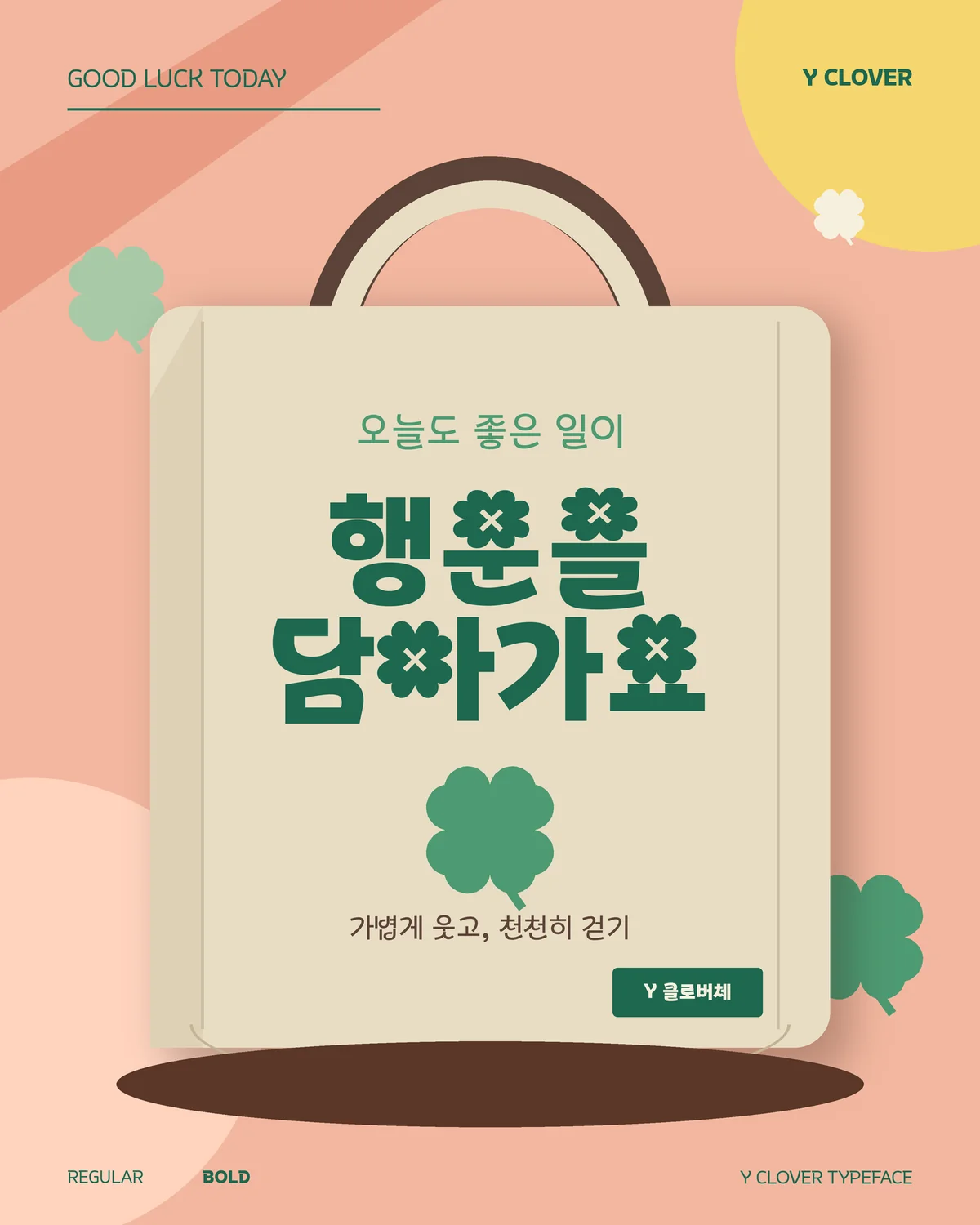
Y클로버체 — (주)케이티에서 배포하는 무료 폰트입니다. 네잎클로버의 형태를 자소에 녹여내 발랄하고 통통 튀는 인상을 표현한 장식 고딕체
KT의 청년 브랜드 Y 서체 시리즈 가운데 2023년에 나온 서체입니다.
모티브는 네잎클로버입니다. KT는 이 서체를 Y의 밝고 활동적인 모습을 네잎클로버에 담은 발랄하고 통통 튀는 서체라고 설명합니다. 행복과 행운이라는 클로버의 상징이 그대로 성격이 된 셈입니다.
굵기는 Regular와 Bold 두 가지이고 현대 한글 11,172자를 모두 담았습니다. 파일에서 재어 보면 자면을 넉넉히 채워 인상이 또렷합니다. 밝고 캐주얼한 이벤트나 프로모션, 아동·청소년 대상 콘텐츠에 어울리고 격식 있는 문서나 긴 본문에는 맞지 않습니다. 누적 다운로드가 7만 건을 넘긴 것으로 알려져 있습니다.